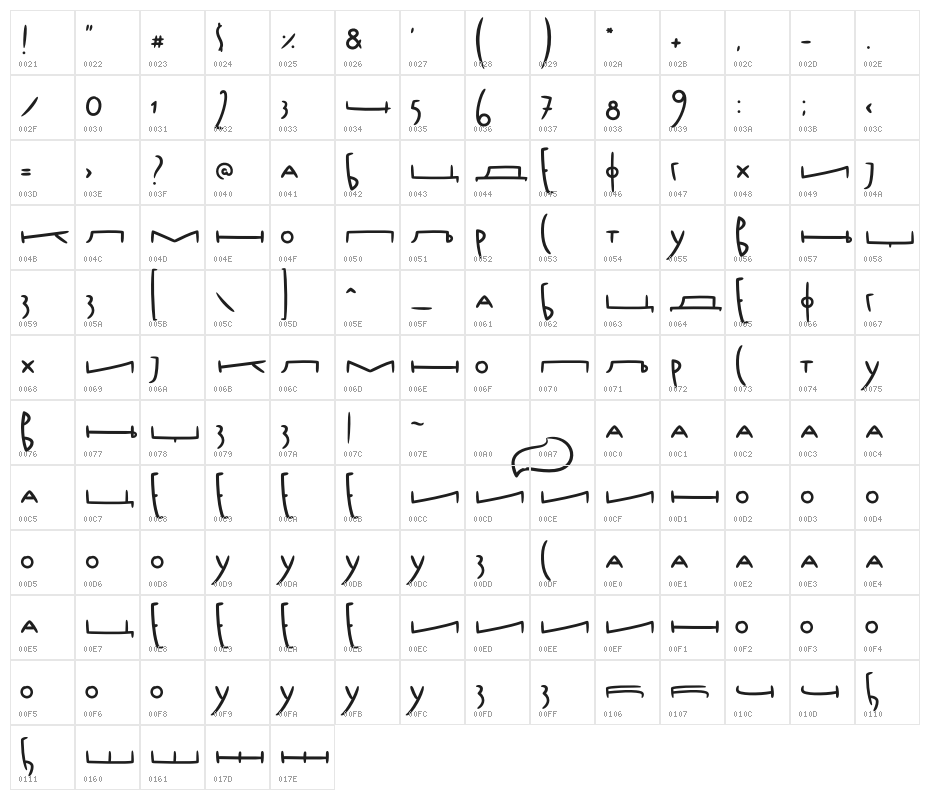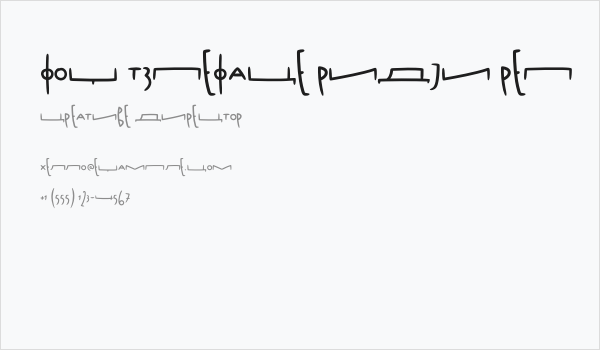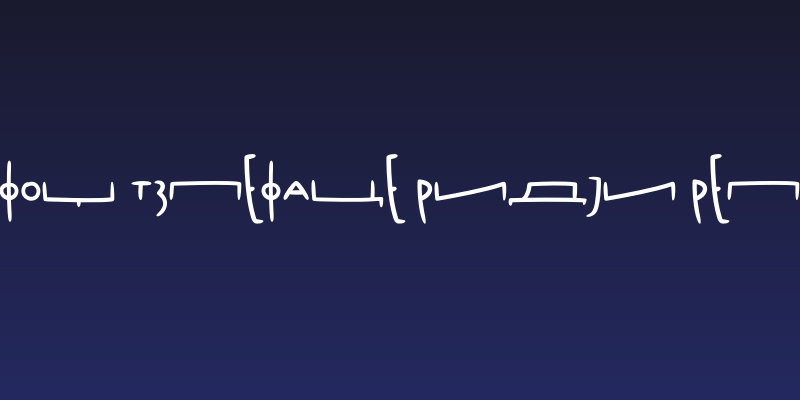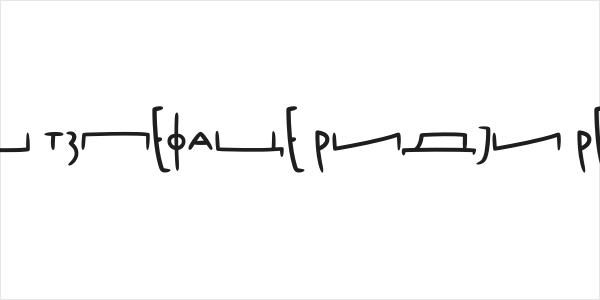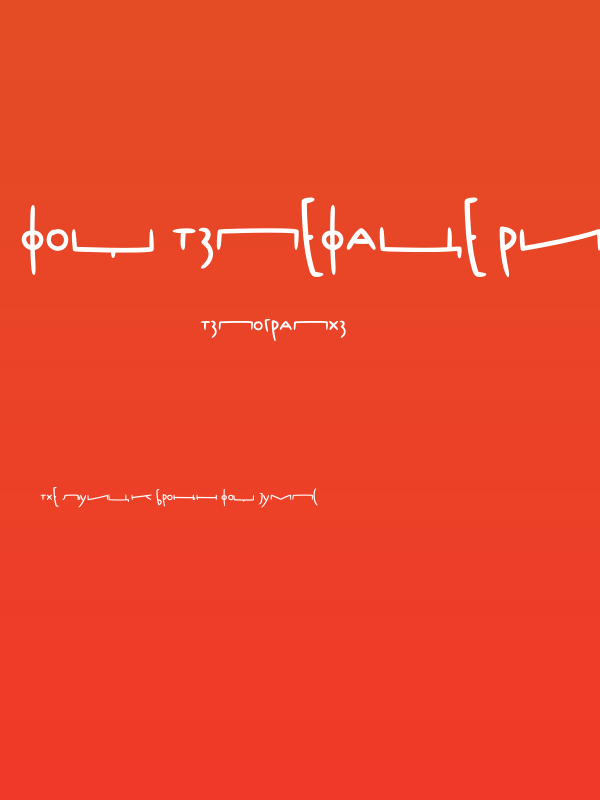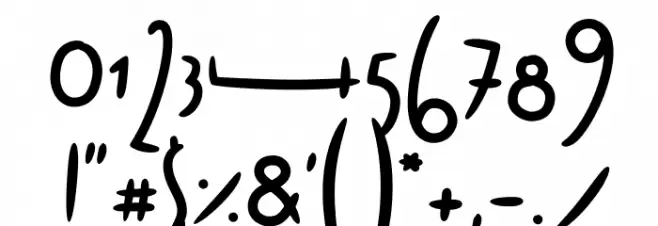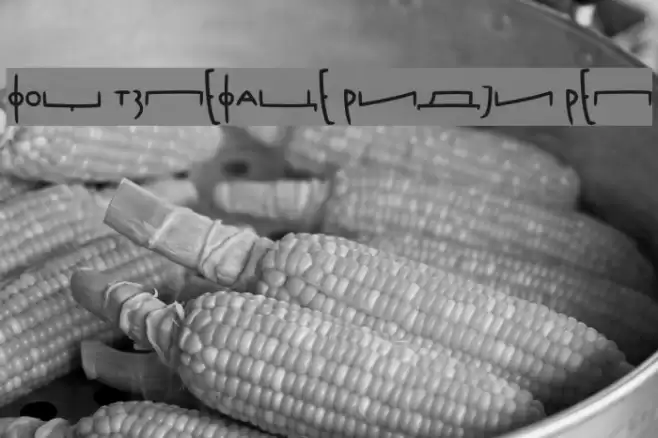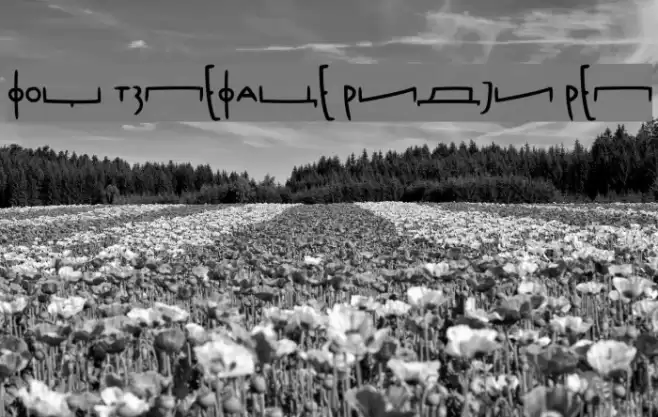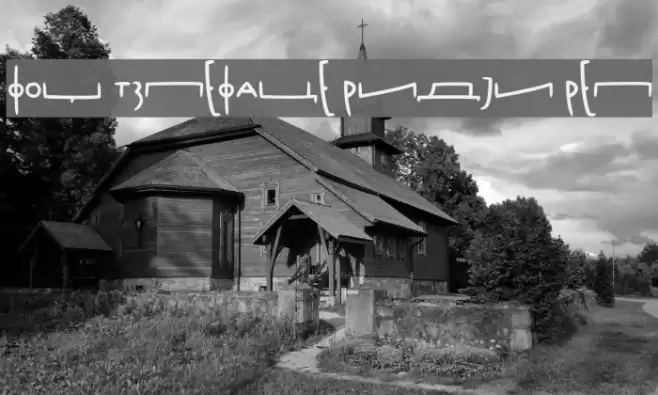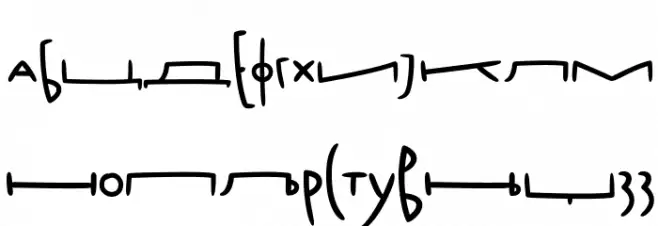
Fox Typeface Ridji Rep Font
| Anwendungsfall | Logos, Posters, Invitations |
| Vorgeschlagene Projekte | Ideal for children's books, creative posters, playful branding, and artistic invitations. |